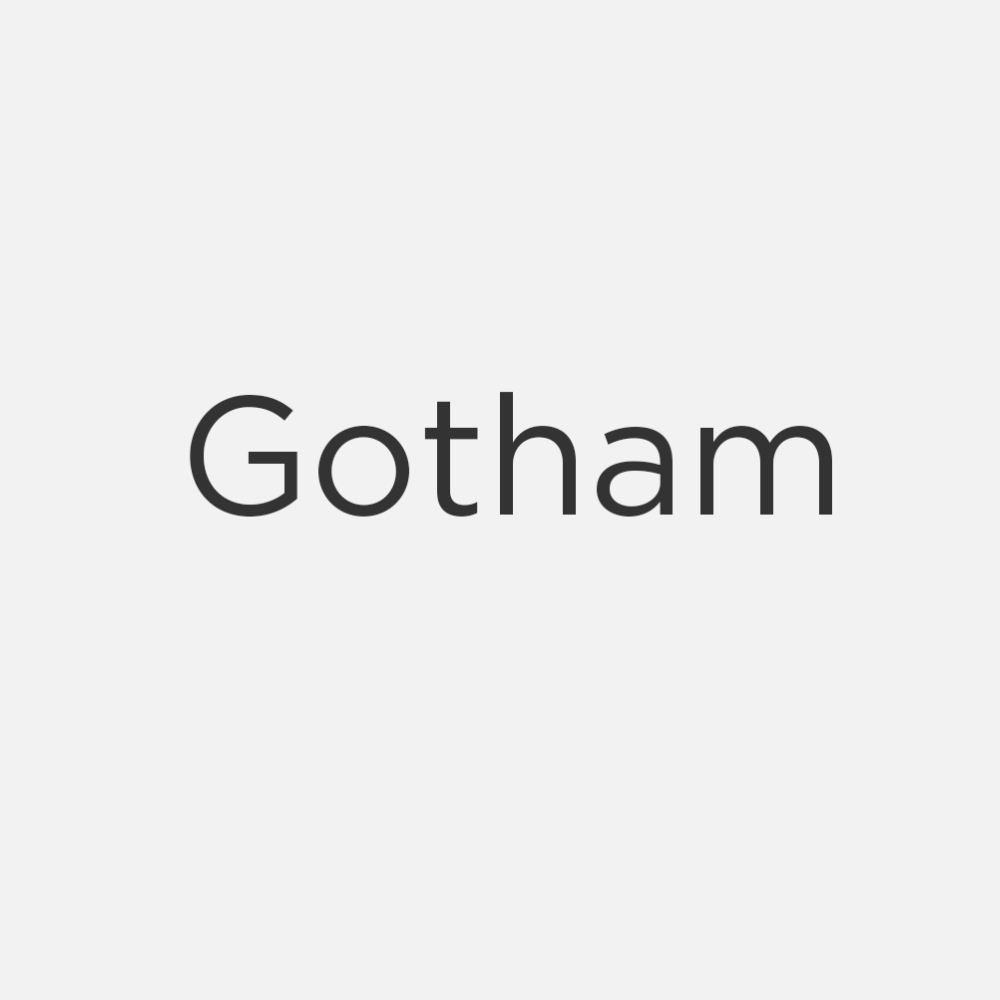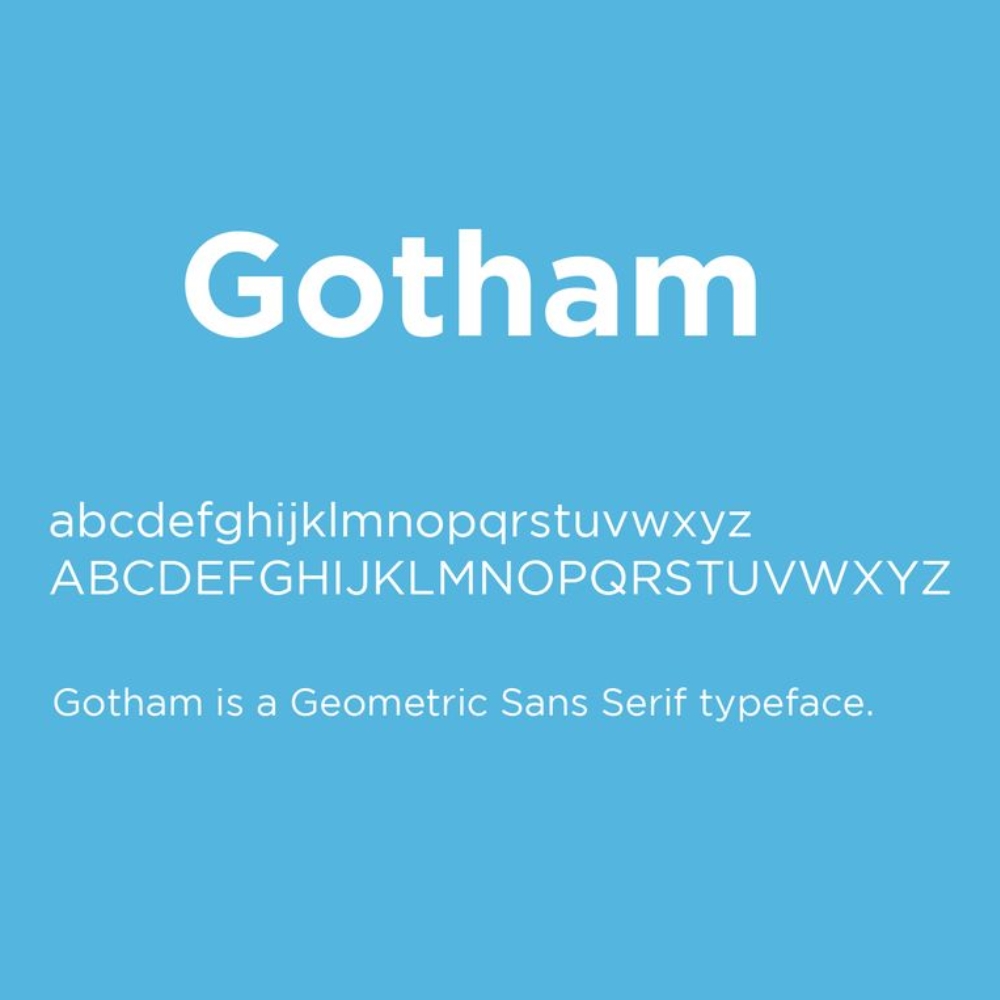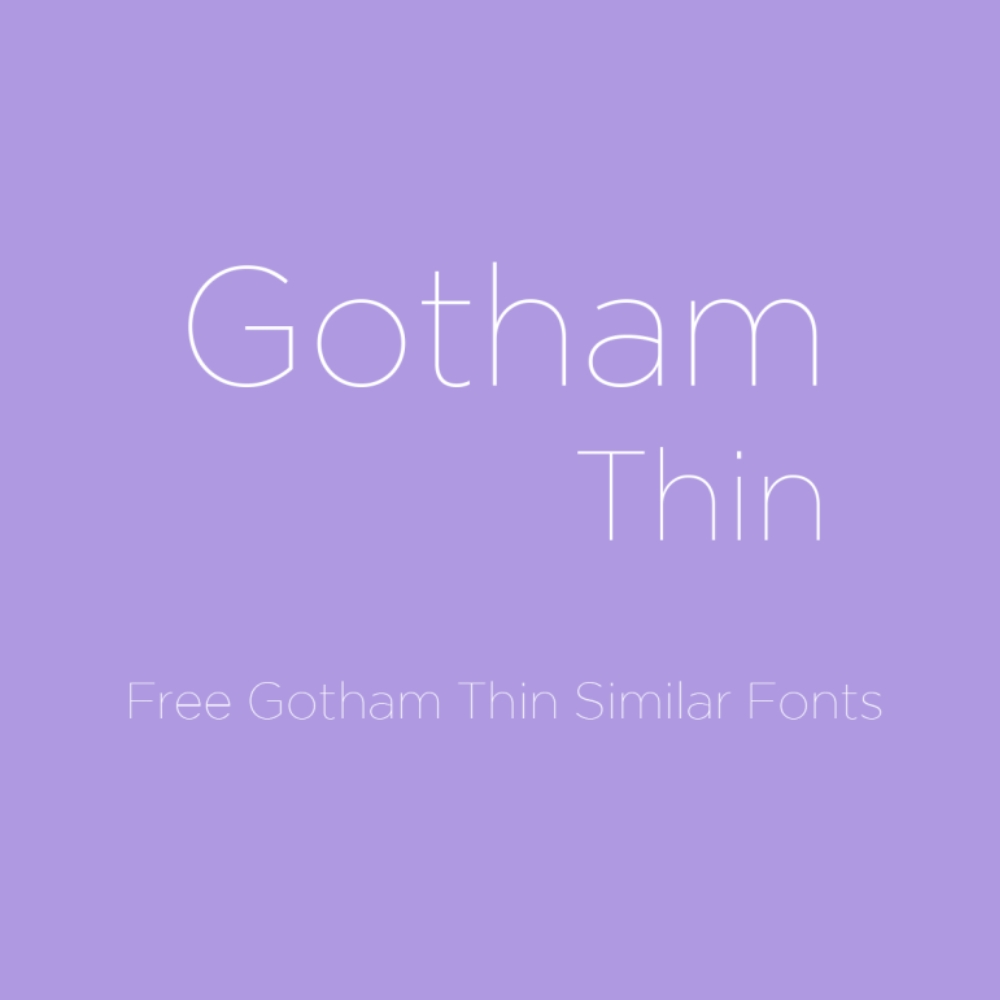
Gotham là một trong những bộ phông chữ Sans-serif mang tính biểu tượng của thế kỷ 21, lấy cảm hứng từ những biển hiệu kiến trúc tại thành phố New York. Với cấu trúc hình học chuẩn xác và vẻ ngoài hiện đại, việc download font Gotham giúp các kiến trúc sư và nhà thiết kế truyền tải thông điệp về sự vững chãi và chuyên nghiệp.
Đặc điểm thẩm mỹ của dòng font Gotham trong thiết kế chuyên nghiệp
Sức hút của Gotham nằm ở sự cân bằng giữa nét vẽ kỹ thuật và tính thẩm mỹ đương đại. Khác với các dòng phông chữ không chân truyền thống, Gotham sở hữu các đường nét thông thoáng, khung chữ rộng và chiều cao ký tự (x-height) được tính toán để tối ưu hóa khả năng đọc. Phiên bản tải font Gotham Việt hóa đã được xử lý tinh tế hệ thống dấu thanh tiếng Việt, đảm bảo các ký tự đặc biệt phối hợp hài hòa với thân chữ, duy trì vẻ đẹp tinh gọn và minh bạch của bộ gốc.
Sự ổn định về mặt thị giác giúp Gotham trở thành lựa chọn ưu tiên cho các nội dung cần độ nhận diện cao. Dù được sử dụng trên các biển hiệu tấm lớn ngoài trời hay trong các ghi chú kỹ thuật nhỏ hẹp, bộ phông vẫn giữ được độ sắc sảo. Đây là giải pháp phù hợp để thể hiện tư duy thiết kế khoa học, phù hợp với phong cách kiến trúc công nghiệp (Industrial) và các giải pháp xây dựng lắp ghép hiện đại đang dẫn đầu xu hướng hiện nay.
| Phân loại phong cách | Geometric Sans-serif / Architectural Style |
| Các biến thể chính | Light, Regular, Bold, Black, Rounded |
Gợi ý lựa chọn: Để bản thiết kế đạt được hiệu quả thị giác ổn định, bạn nên tải font Gotham Bold cho các đầu mục quan trọng và kết hợp cùng kiểu Regular cho phần nội dung thuyết minh. Nếu dự án hướng đến sự thân thiện, việc tải font Gotham Rounded sẽ là phương án hiệu quả để làm mềm các hình khối kiến trúc vuông vức.
03 Ứng dụng phông chữ Gotham vào thực tế xây dựng
Nhờ diện mạo khoa học và vững chãi, việc sử dụng các kiểu chữ từ tải font Gotham mang lại giá trị thực tế cao trong quá trình triển khai dự án hiện đại:
- Hệ thống nhận diện cho văn phòng & nhà xưởng: Những nét chữ hình học của Gotham rất ăn ý khi xuất hiện trên biển tên công ty hoặc bảng chỉ dẫn tại các khu văn phòng container. Phông chữ này giúp công trình toát lên vẻ chuyên nghiệp và uy tín đối với đối tác.
- Hồ sơ năng lực dự án (Profile): Sử dụng download font iCiel Gotham giúp trình bày thông tin dự án, thông số vật liệu panel cách nhiệt một cách mạch lạc, tạo ấn tượng về một đơn vị có quy trình vận hành bài bản.
- Trang trí không gian nội thất tối giản: Bạn có thể dùng font Gotham để cắt chữ nổi laser hoặc in decal trang trí tường tại sảnh chờ, phòng họp nhằm tạo điểm nhấn hiện đại và khơi gợi cảm hứng làm việc năng động.
03 Lưu ý kỹ thuật khi trình bày bố cục với tải font Gotham Việt hóa
Để khai thác hiệu quả vẻ đẹp của dòng font Sans-serif cao cấp này mà không làm giảm tính chuyên nghiệp của bản thiết kế, người dùng nên lưu tâm một số kinh nghiệm sau:
- Kiểm soát độ nhấn thị giác: Hãy tận dụng biến thể Gotham Black free download font cho các từ khóa cực kỳ quan trọng hoặc các biển cảnh báo an toàn công trường để thu hút sự chú ý nhanh nhất từ người xem.
- Cân đối khoảng cách dòng: Do cấu trúc chữ Gotham có phần rộng ngang, bạn nên thiết lập khoảng cách dòng thoáng một chút để văn bản không bị bết dính, đặc biệt là trong các tài liệu báo giá hoặc thuyết minh kỹ thuật dài.
- Đồng bộ hóa trong hồ sơ thiết kế: Hãy duy trì sử dụng gia đình font Gotham từ bản vẽ phối cảnh đến slide trình chiếu để tạo nên sự thống nhất trong hình ảnh thương hiệu của đơn vị thiết kế và thi công.